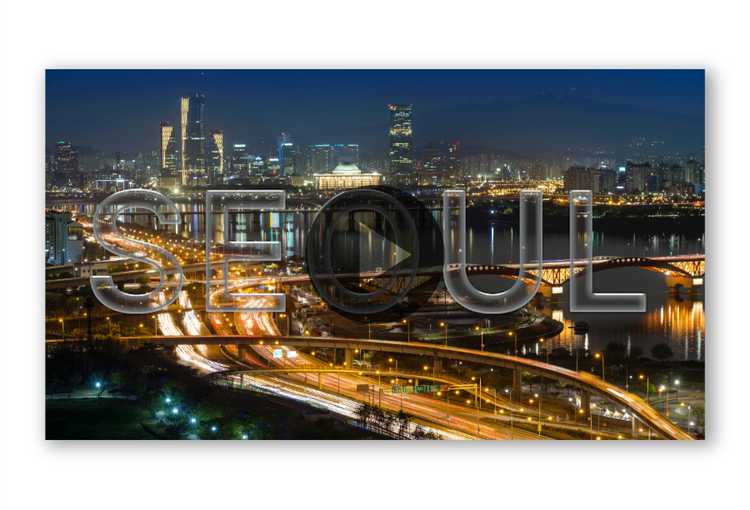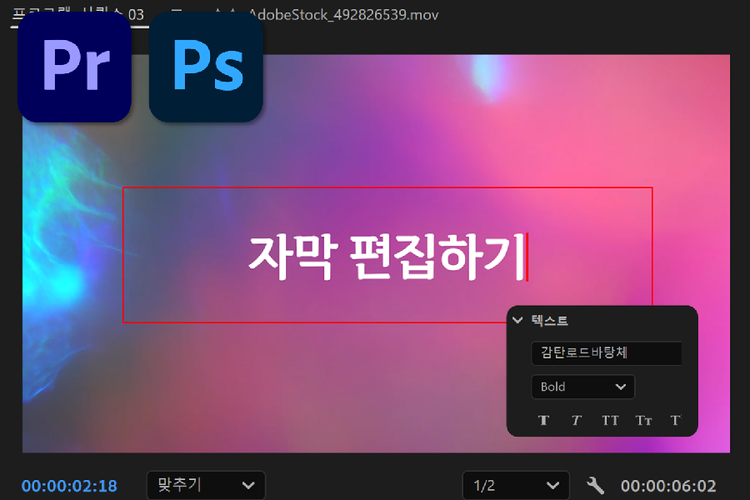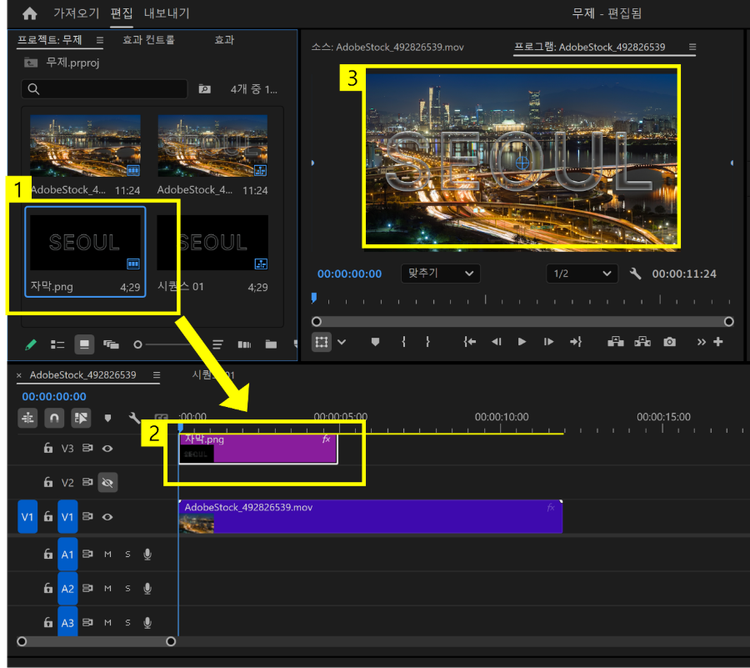
영화 자막 폰트 추가하고 영상에 자막 넣기
자막은 영상의 분위기를 좌지우지하는 큰 요인 중 하나인데요. 그렇기 때문에 영상 분위기에 맞는 자막의 폰트를 사용하는 것이 영상 제작에 있어 매우 중요합니다. 하지만, 영상을 제작할 때 영상과 어울리는 자막을 찾지 못해 아쉬웠던 경험이 있을 텐데요.
이제 어도비 프리미어 프로(Adobe {{premiere}})에서 제공하는 다양한 폰트 사용하여 동영상 자막 추가해 보세요. 원하는 느낌의 폰트가 없다면 어도비 폰트에서 다운로드하여 프리미어 프로에서 사용할 수 있습니다. 이제 이 튜토리얼을 따라 원하는 자막 폰트 찾고 영상에 자막 추가해 보세요.
1. 어도비 프리미어 프로에서 제공하는 기본 폰트 사용하기
어도비 프리미어 프로(Adobe {{premiere}})에서는 제공하는 기본 폰트 사용하여 동영상 자막 추가해 보세요. 예를 들어, 프리미어 프로에서 제공하는 기본 폰트 [영화 웹 캡션]를 사용하여 영상 제작하면 영화 특유의 클래식한 분위기를 연출할 수 있습니다. 원하는 영화 자막 폰트를 이용하여 영상 제작해 보세요.
프리미어 프로에서는 [영화 웹 캡션]뿐만 아니라 다양한 기본 폰트를 제공하고 있습니다. 이제 상단 패널에서 [그래픽] > [찾아보기]를 선택하여 더 많은 기본 폰트를 확인해 보세요.
2. 어도비 폰트 사용하기
프리미어 프로에서 제공하는 기본 폰트 중 원하는 느낌의 폰트가 없다면 어도비 폰트에서 새로운 폰트 다운로드하여 프리미어 프로에 추가하고 자막으로 사용해 보세요.
3. 자막에 폰트 입히기
이제 추가한 글꼴을 사용하여 영상 자막을 달아보세요. 상단 패널에서 [그래픽] > [편집]을 선택해 주세요. 글꼴 활성화를 했다면 텍스트 패널에서 추가한 글꼴을 찾을 수 있습니다. 추가한 글꼴을 찾아 자막에 적용해 주세요. 손쉽게 원하는 폰트로 프리미어 프로 자막 넣기 할 수 있습니다.
위와 같은 방법으로 원하는 영화 자막 폰트 찾고 프리미어 프로 폰트 추가하여 영상 자막 달아보세요. 어도비 프리미어 프로를 사용하면 어도비 폰트에서 제공하는 다양한 폰트를 사용하여 동영상 만들기 할 수 있습니다. 또한, 동영상 배경음악 추가 및 편집 등 다양한 동영상 편집 기능을 제공하고 있어 손쉽게 동영상 편집 가능합니다.